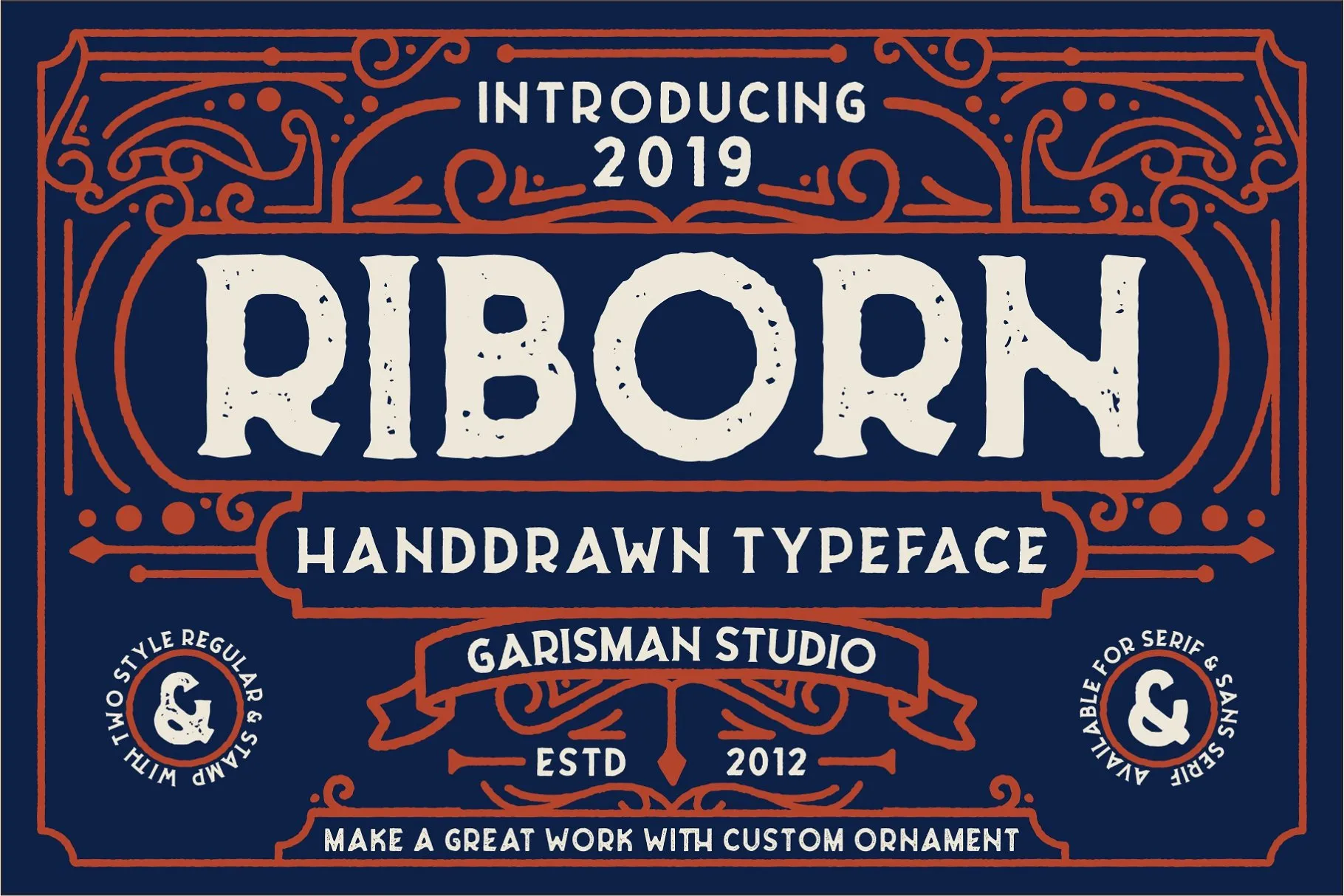
Riborn Typeface – Download Grátis
A Riborn Typeface é uma nova adição à coleção das fontes display do M.0Type, inspirada nas linhas finas e vintage da Garisman Std. Com sua mistura única de estilos sóbrios e marcantes, essa fonte destaca-se como um recurso versátil para designers. Riborn Typeface apresenta quatro diferentes tipos de fonte, batizada cada uma com o termo “ribs”, que poderão ser usadas em trabalhos diversos, desde logos ou tipografia até a criação de letras a mão e estampas de camisetas. Perfeita para aqueles que buscam um estilo vintage modernizado, esta fonte traz à tona uma mistura atemporal de linhas finas com detalhes trabalhados. Suas sutilezas podem ser aproveitadas em projetos como cartazes e identidades de marca, enquanto sua forte característica permite estender a elegância para outros formatos de design, incluindo embalagens, rótulos e até mesmo criações gráficas em camisetas. Seja você um designer de letras a mão ou uma marca buscando adicionar um toque único em suas camisas, a Riborn Typeface oferece o poder necessário para tornar seu trabalho ainda mais único e memorável. Composta por quatro tipos distintos de fonte, esta família de tipos permite aos designers explorarem sua variedade enquanto criam trabalhos que vão além das fronteiras tradicionais do design.